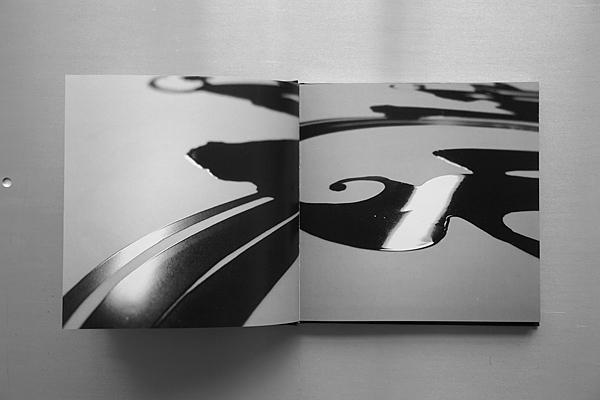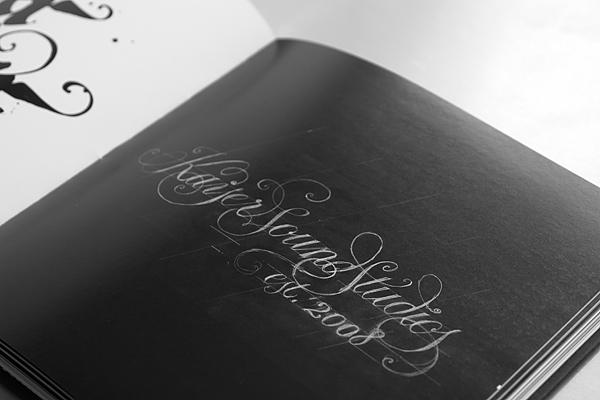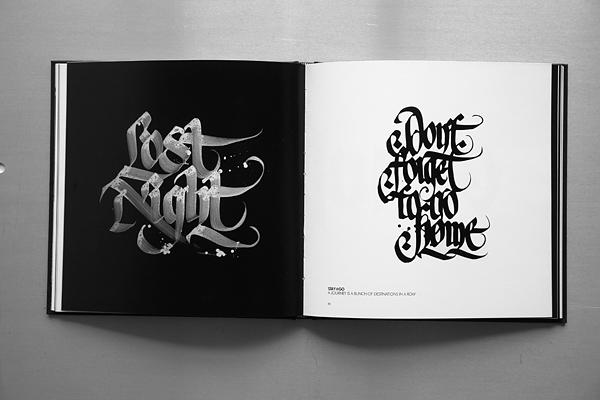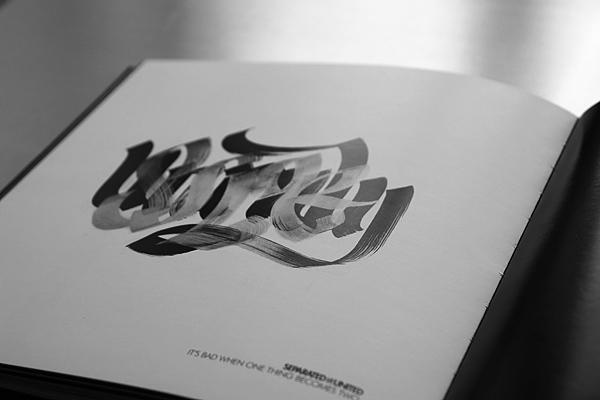
Der niederländische Künstler Niels (Shoe) Meulman hat mit Calligraffiti seinen ganz eigenen Stil geschaffen. Wie das Kunstwort vermuten lässt, verbindet er die Formprinzipien klassischer Kalligrafie mit den Stilmitteln der Graffiti-Szene: tropfende Farben, verschlungene Buchstabenformen und schnelle Pinselstriche, die aussehen, als wären sie mit einer Spraydose in Eile auf eine Häuserwand aufgebracht worden. Das durchgängig schwarz-weiße Buch — teilweise mit Spotlack veredelt — ist eine Retrospektive des künstlerischen Schaffens. In der Biografie erfährt der Leser, wie Meulman mit 12 Jahren sein erstes Calligraffiti in Form des Schriftzuges Shoe mit einem Edding auf eine Mauer in Amsterdam malte. Heute verkaut er seine Schriftkunst für 100 bis 2000 Euro. Der überwiegende Teil des Buches ist dann den Werken — meist einzelnen Schriftzügen — gewidmet, die jeweils auf einer Seite einzeln präsentiert werden. Im Anhang werden die Herstellung, Material und Einsatz der Arbeiten kurz erläutert.
Untertitel: The Graphic Art of Shoe